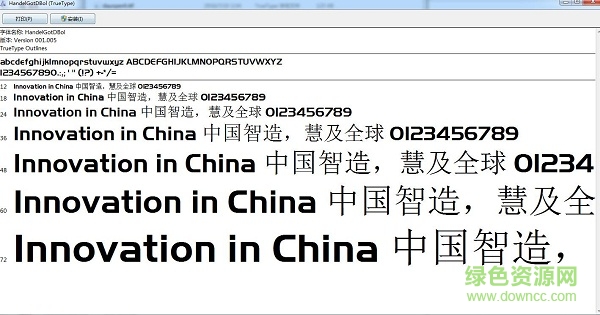
handelgotdbol-普通(西方)
handelgotdbol是什么字體?handelgotdbol-普通(西方)是一款多用于屏幕顯示的無襯線字體,和灰度雅黑字體非常相似,字形扁方筆畫簡潔,顯示效果非常清晰,歡迎大家免費下載!
handelgotdbol字體特點
handelgotdbol字體非常的飽滿和優(yōu)美,支持高清顯示的ClearType功能,在同樣的字號下,單字面積就顯得更大,更容易識別,閱讀起來也更舒服。